Halloween è ormai diventato un evento popolare in tutto il mondo, celebrato con feste, decorazioni, e ovviamente, grafica a tema. Che si tratti di progettare un invito per una festa, creare un post inquietante sui social o dare vita a un sito web dall’aspetto sinistro, i font possono giocare un ruolo fondamentale.
I font Halloween sono strumenti preziosi per ogni designer o appassionato di grafica che vuole suscitare emozioni specifiche, dai brividi alla paura, ma anche un tocco di divertimento “sinistro” e un po’ giocosamente macabro.
Ma cosa rende un font “da Halloween”? Questo tipo di carattere tipografico sfrutta vari stili visivi per trasmettere atmosfere spaventose, evocare antiche leggende o aggiungere un pizzico di mistero. Vediamo i principali stili di font Halloween e il tipo di emozione che possono suscitare.
I diversi stili dei Font Halloween (e quali emozioni comunicano)
I font per Halloween possono essere divisi in diverse categorie stilistiche. La scelta dello stile giusto dipende dall’effetto che si vuole ottenere: dall’eleganza gotica, alla paura autentica, fino a un senso di divertimento dark.
Font Halloween di stile Gotico
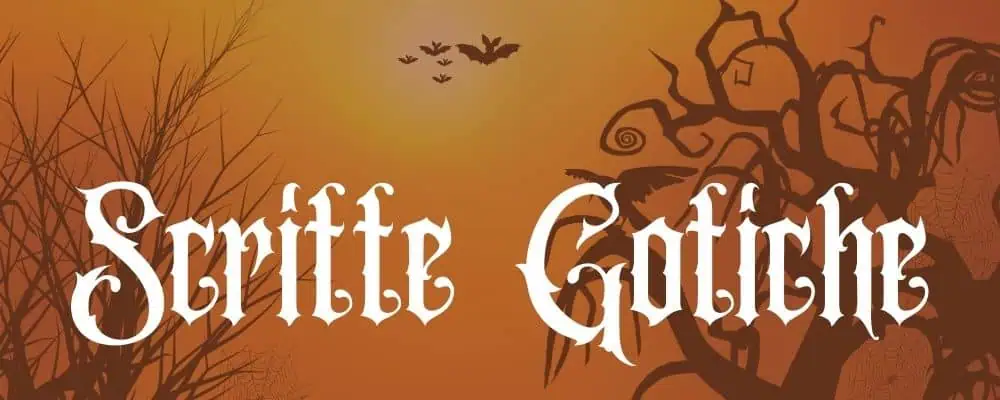
I font gotici sono perfetti per evocare atmosfere medievali, chiese abbandonate e antiche leggende. Spesso caratterizzati da lettere affilate e intricate, questi font si ispirano allo stile calligrafico del Medioevo, rendendoli ideali per ambientazioni da brivido ma anche sofisticate.
Sono molto usati per titoli di film o libri horror, poiché infondono un senso di inquietudine e maestosità al tempo stesso. Con questi font si vuole comunicare una paura più sottile, quasi rispettosa, ideale per un tono di Halloween gotico e raffinato.
Font Halloween “sanguinanti” e “gocciolanti”
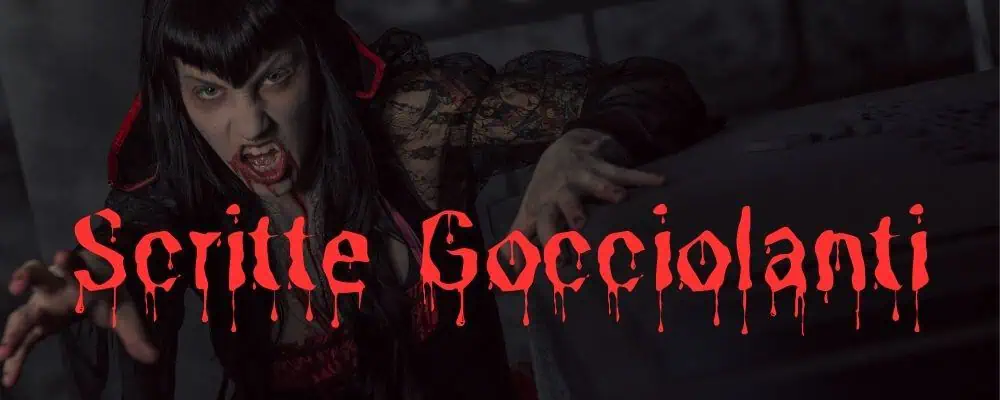
I font gocciolanti richiamano l’immagine del sangue o di altri “liquidi sinistri” che colano. Spesso sono usati per progetti che vogliono evocare un effetto di terrore e disgusto, come il titolo di un film splatter o un volantino per una casa infestata.
Questo tipo di font suggerisce qualcosa di macabro e disturbante, e si presta per contesti dove si vuole accentuare la paura con un tocco grafico cruento. Perfetti per locandine horror, siti web dedicati al genere splatter, o anche per copertine di libri spaventosi.
Font Halloween in stile “scrittura spettrale”
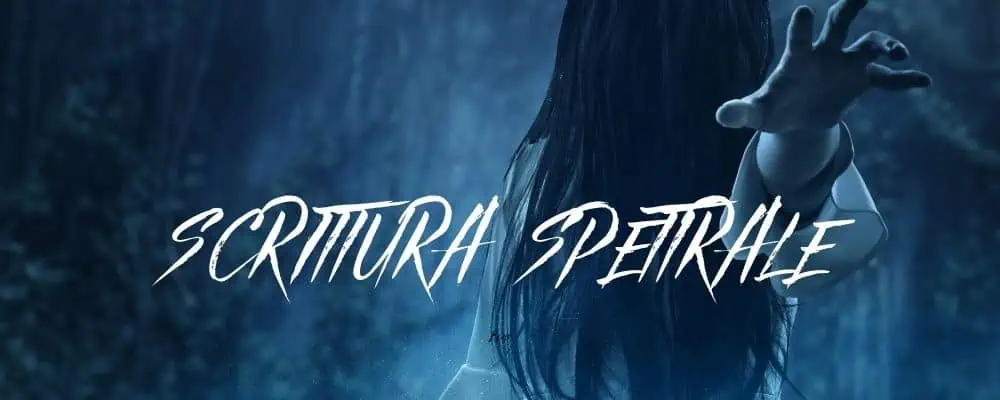
Questo stile simula la scrittura a mano irregolare, come se fosse stata scritta con un gesso o un pennarello da qualcuno in preda al panico.
Le linee non sono perfettamente dritte, e spesso il tratto sembra tremante o strappato, dando l’impressione di un messaggio lasciato in fretta in un contesto di tensione. I font di questo tipo sono ideali per comunicare un senso di ansia, angoscia e paura.
Font Halloween minimalisti e oscuri
Alcuni font Halloween adottano un approccio più sottile e oscuro, usando linee sottili e dettagli che suggeriscono il terrore senza essere espliciti. Questo stile è perfetto per chi cerca di evocare un senso di mistero e sospensione. Ideale per progetti che richiedono un tocco di eleganza spettrale senza cadere nel cliché del sangue e delle ossa.
Questi font sono molto versatili, adatti per contenuti a tema o per siti web che vogliono suggerire una “presenza” senza renderla esplicita.
Font Halloween decorativi e divertenti
Non tutto ciò che riguarda Halloween deve essere terrificante! Molti font Halloween combinano elementi giocosi con dettagli macabri, come zucche, ragni, pipistrelli o cappelli da strega sulle lettere. Questi font decorativi sono perfetti per creare un’atmosfera giocosa e divertente, adatta a un pubblico di tutte le età, comprese le famiglie e i bambini.
Questo stile rende Halloween più accessibile e meno spaventoso, ideale per inviti a eventi scolastici, feste in costume, o social media che mirano a coinvolgere un vasto pubblico in modo più scherzoso che orrorifico.
I migliori font per grafiche spettrali e mostruose per la festa di Halloween
Ecco una lista di font spaventosi che possono essere scaricati gratuitamente, perfetti per dare ai tuoi progetti quel tocco horror di cui hai bisogno.
Creepster
Creepster è il font ideale per chi desidera creare progetti di stile Horror. Creato da Squid e Sideshow, questo font ha un aspetto ispirato alle lettere in stile “blob” che ricorda alcuni titoli classici dei film horror degli anni ’50 e ’60.
Da un punto di vista visivo Creepster è caratterizzato da linee e curve irregolari che gli conferiscono un aspetto tremolante e sinistro. Ogni lettera ha un profilo unico con gocce raccapriccianti che pendono dalle estremità. Il font contiene numerose varianti per ciascun carattere, rendendo possibile una personalizzazione notevole.
È quasi come “creare il proprio mostro” ogni volta che si scrive, grazie alla varietà di glifi alternativi.
Zombie Holocaust
Zombie Holocaust è un font iconico e spaventoso, creato traendo ispirazione dal celebre film “Il giorno dei Morti” di George Romero. Ogni lettera sembra logorata, come se fosse stata graffiata o mordicchiata da un’orda di non morti, conferendo al testo un look autenticamente “apocalittico”.
Ghost Clouds
Ghost Clouds, creato da Xerographer Fonts, è un font dall’aspetto etereo che evoca l’immagine di nuvole fantasmagoriche che fluttuano nell’aria. Con le sue linee irregolari e le lettere che sembrano volare, questo font crea un effetto divertente e misterioso, come se fosse stato scritto da una presenza soprannaturale. Il suo design è molto amichevole e risulta adatto a progetti grafici leggeri e divertenti.